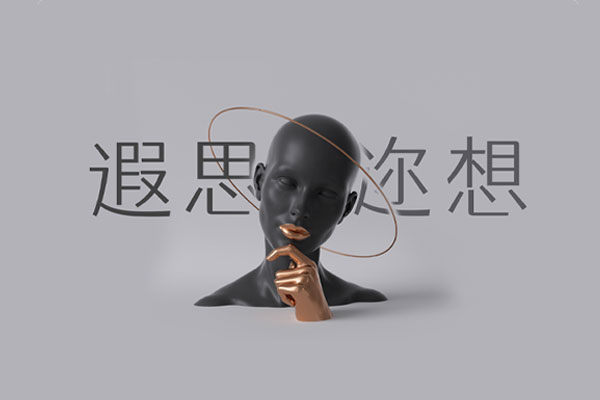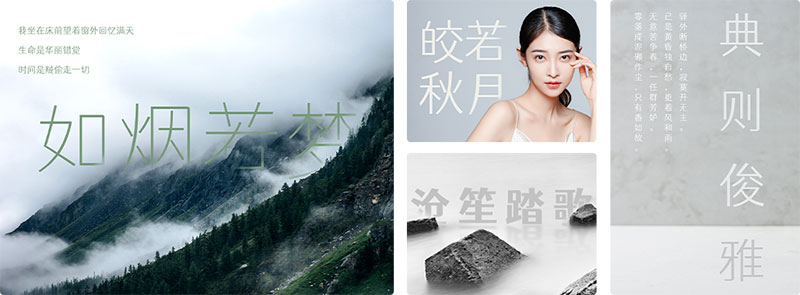
站酷仓耳渔阳体
站酷仓耳渔阳体(又名仓耳渔阳体)是设计师张少龙创作的简体中文字体,具有5个不同的字重。这款字体是仓耳字库在2020年新冠疫情期间为造福社会推出的一份珍贵礼物,也是站酷冠名的首款拥有家族字体的公益字库。
站酷仓耳渔阳体的字形融合了宋体和黑体的结构特点,将部分笔画转折处进行了圆角处理,使得字体方圆结合,厚重而又不失活泼灵动。家族字体包含5个不同字重,均免费供全社会使用(包括商业用途)。该字体于2020年9月发布了第一版。
站酷仓耳渔阳体效果预览